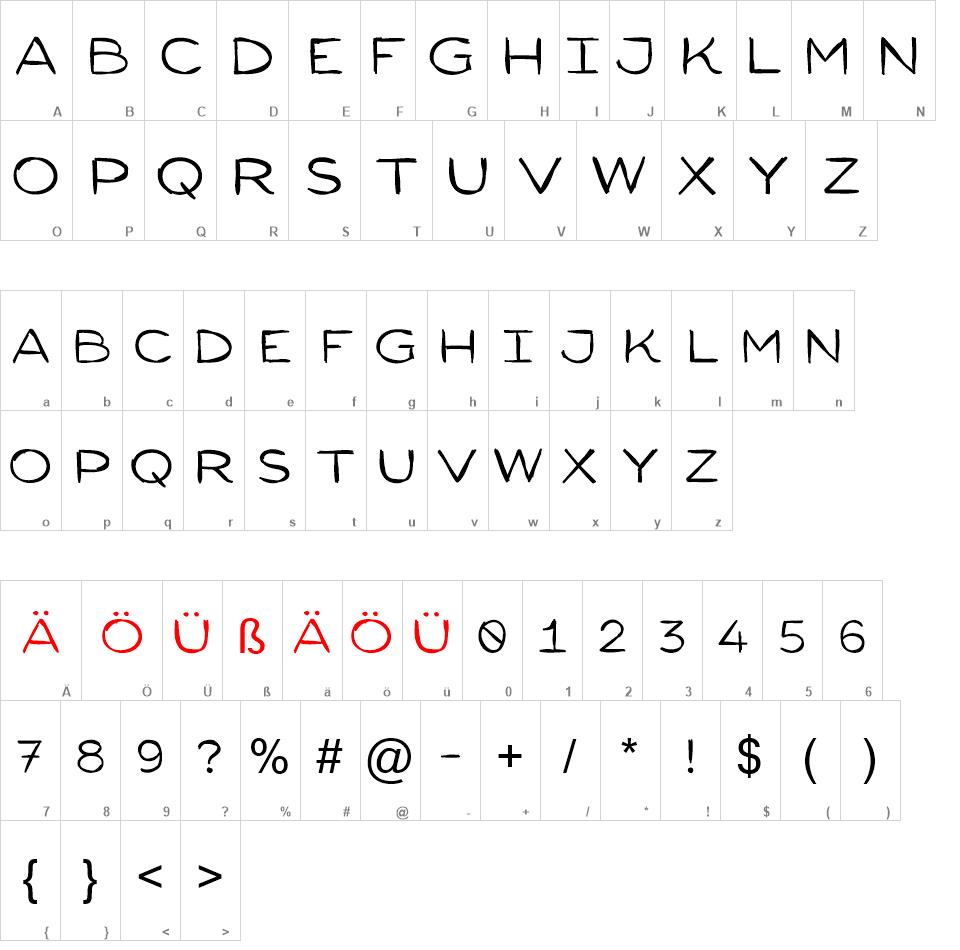
Sensa
Sensa font
Sensa ist eine handgefertigte Schriftfamilie mit 21 Schriftarten. Die Sensa-Bürste ist in 6 Unterfamilien unterteilt, die zu einer breiten Palette an visuellen Fähigkeiten beitragen, darunter Sensa Pen, Sensa Wild, Sensa Sans, Sensa Serif und Sensa Goodies.
Die Grenze ist nur Ihre Vorstellung. Hält alle Schriftarten vor und begleitet den Rest der Schriftarten problemlos. Um in allen möglichen Kombinationen zusammenzuarbeiten, wurden alle Schriftarten in diesem Paket mit dieser einfachen Idee erstellt.
Sensa gilt für jedes Design-Projekt, von Werbung über Verpackung, Redaktion und Branding bis hin zu Web- und Screen-Projekten. Sie haben eine große Auswahl für eine Schönheit und ein Gefühl von Zärtlichkeit oder mehr Männern und eine starke Kommunikation.